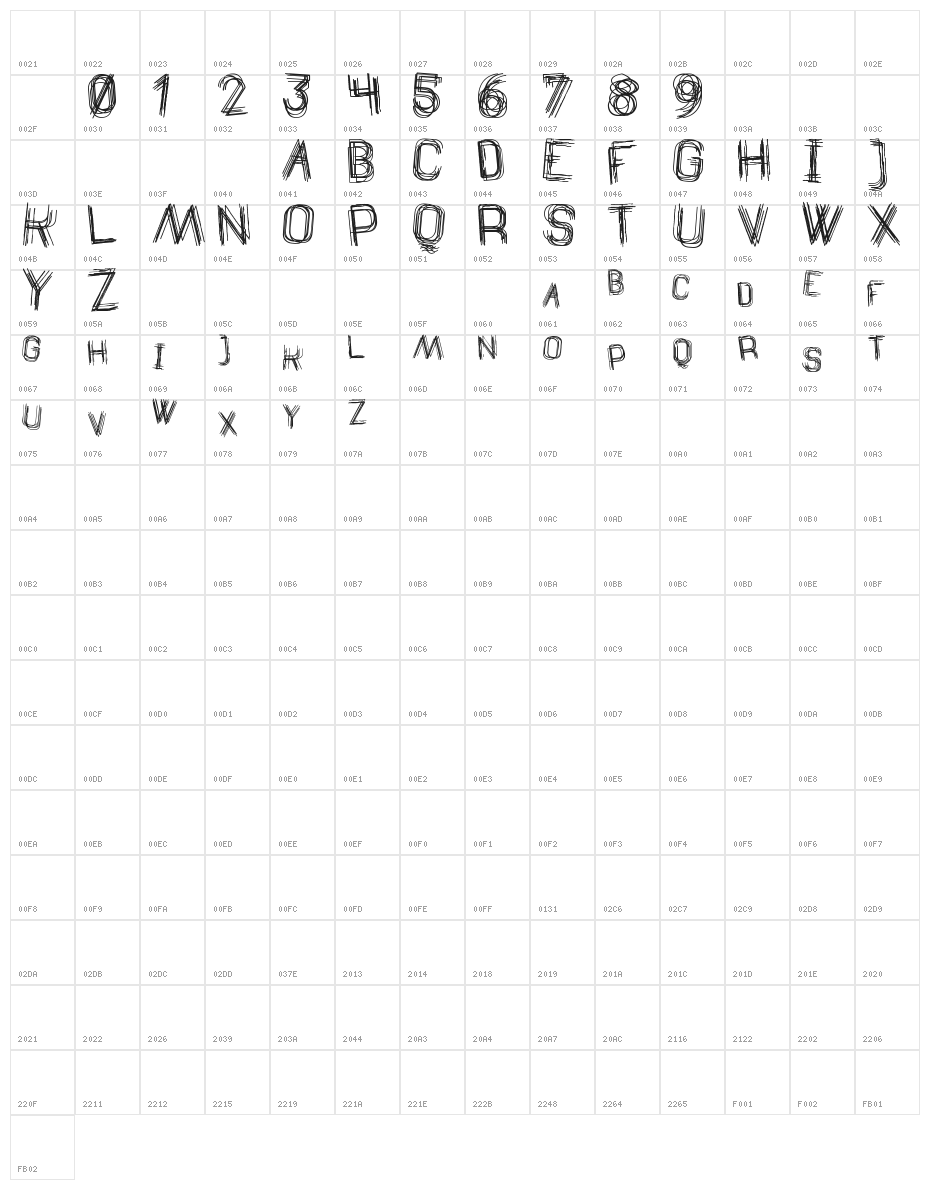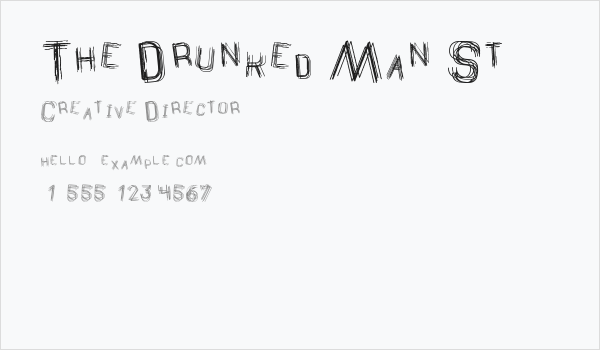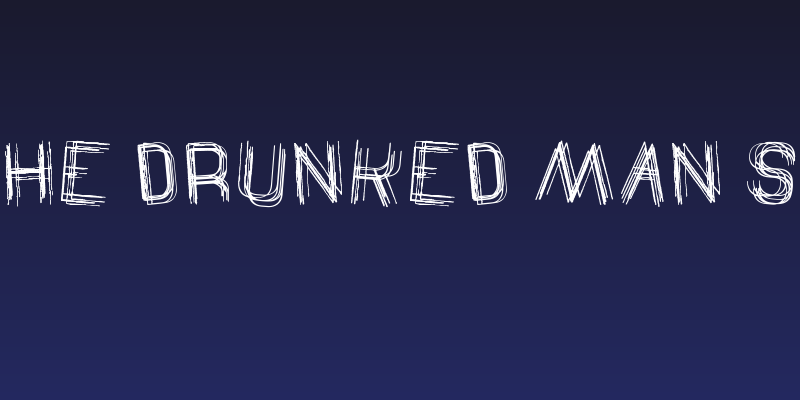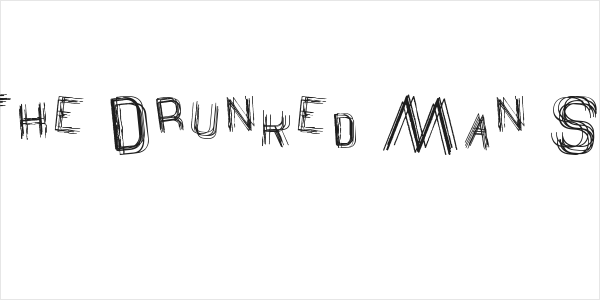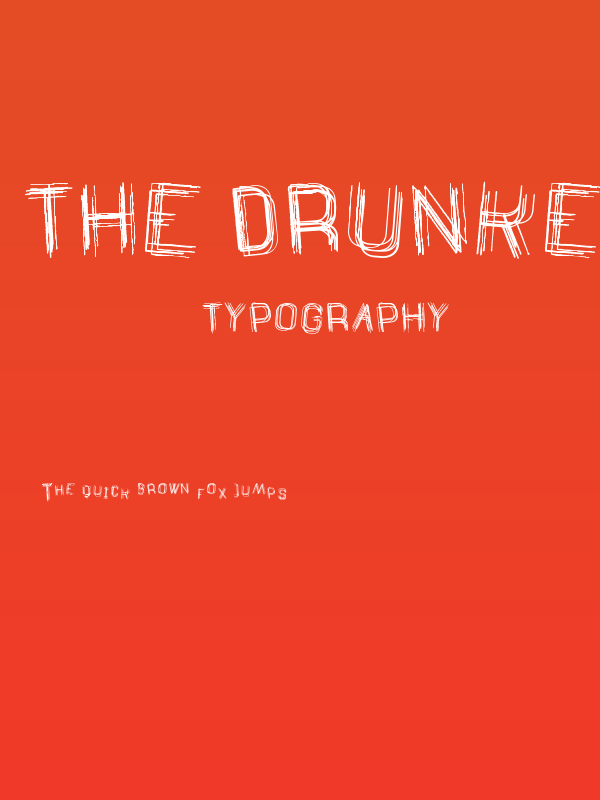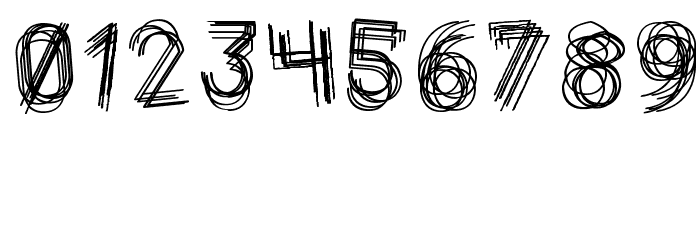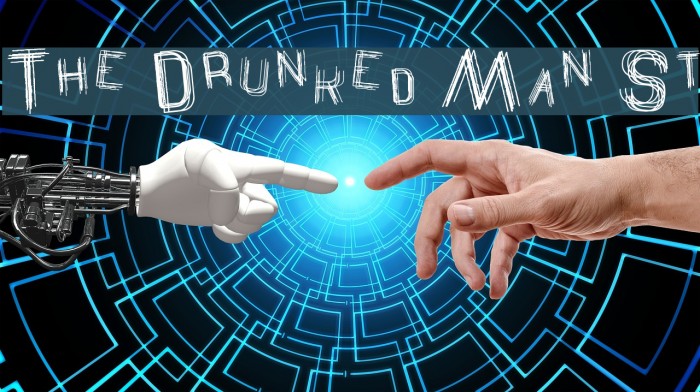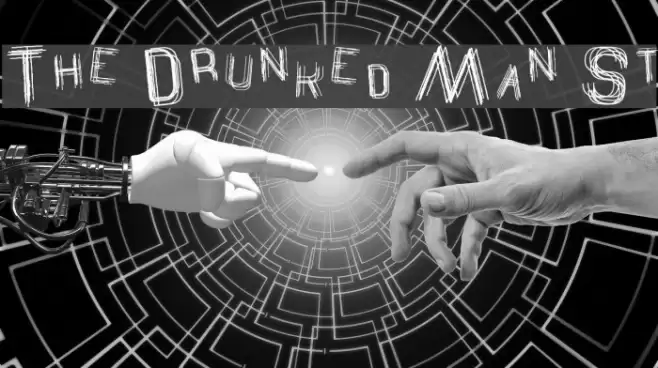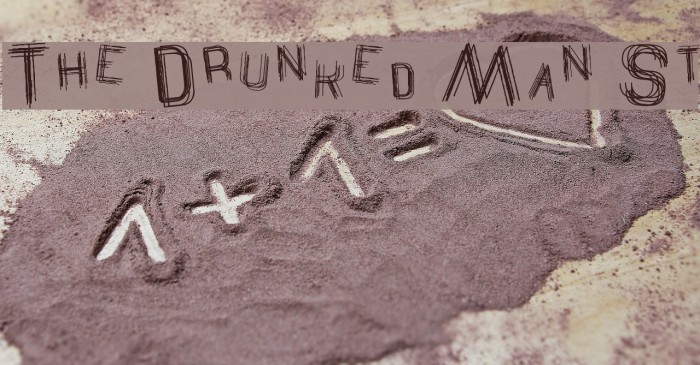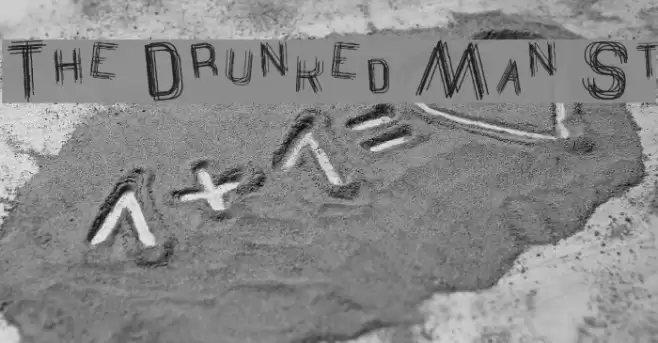
The Drunked Man St Font
✎ Distorted Eroded
| Vorgeschlagene Projekte | Ideal for artistic projects, informal posters, creative branding, and any design needing a bold, unconventional look. |